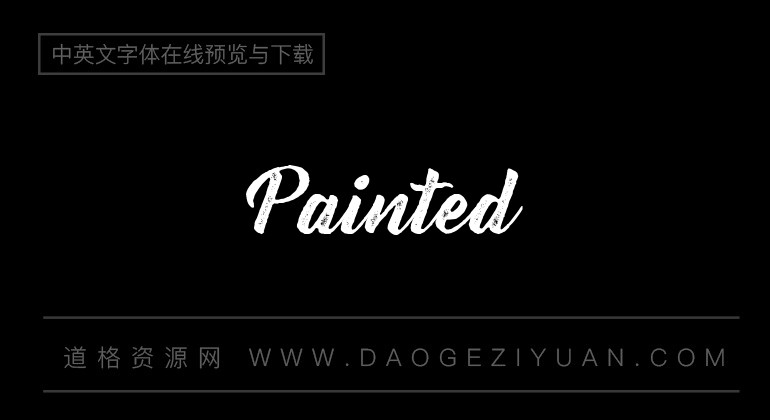
Painted 字体是一种漂亮的艺术字体,它的特点是字体细节的描绘,字体的每个字母都有自己的风格,比如有的字母是抽象的,有的字母是自然的,有的字母是抽象内容介绍
Painted是一款非常不错的手写艺术字体,具有很好的视觉感,适合于文化类的宣传设计、商业类品牌的广告和产品包装设计以及个性化文字排版等较多场景。